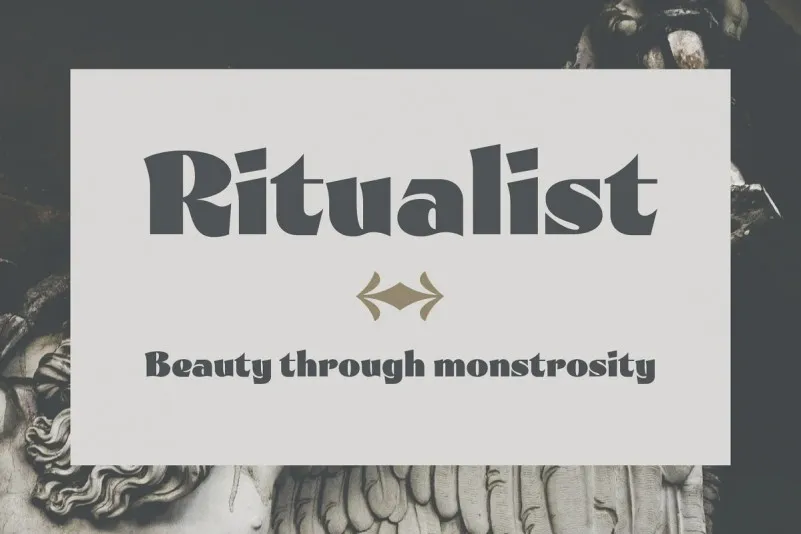
A ‘Ritualist Display Font’ é uma opção perfeita para quem busca destaque visual e simplicidade no design de materiais publicitários. Inspirada num estilo urbano simples e moderno, esta fonte estendida transmite atitude com força quando usada como texto capa. Ideal para criar logos, logomarcas, embalagens, outdoors e designs para camisas customizadas, a ‘Ritualist’ é uma escolha inteligente para qualquer projeto que exige um estilo inconfundível e atemporal. Seja você criando a identidade visual de uma marca ou montando sua própria coleção de arte digital, esta fonte vai ajudá-lo a destacar-se.